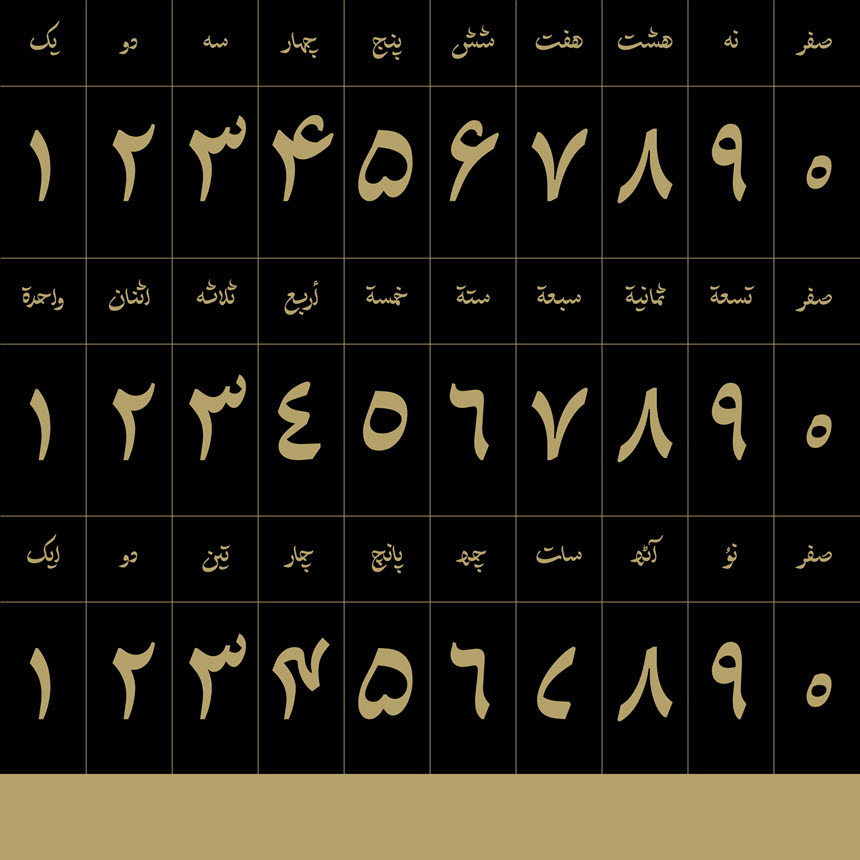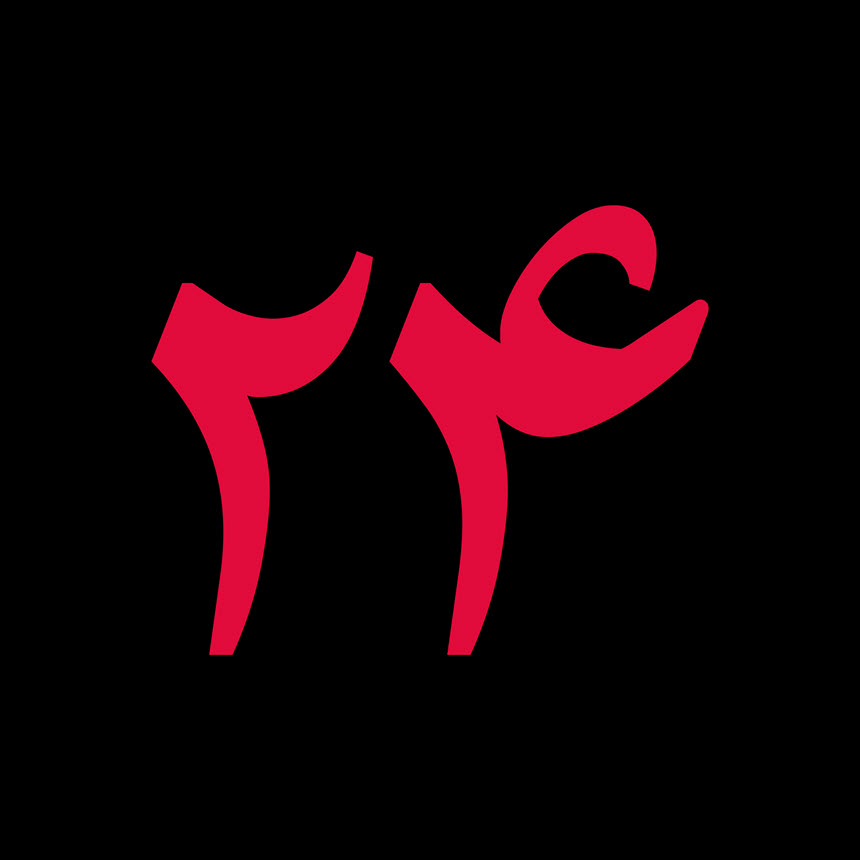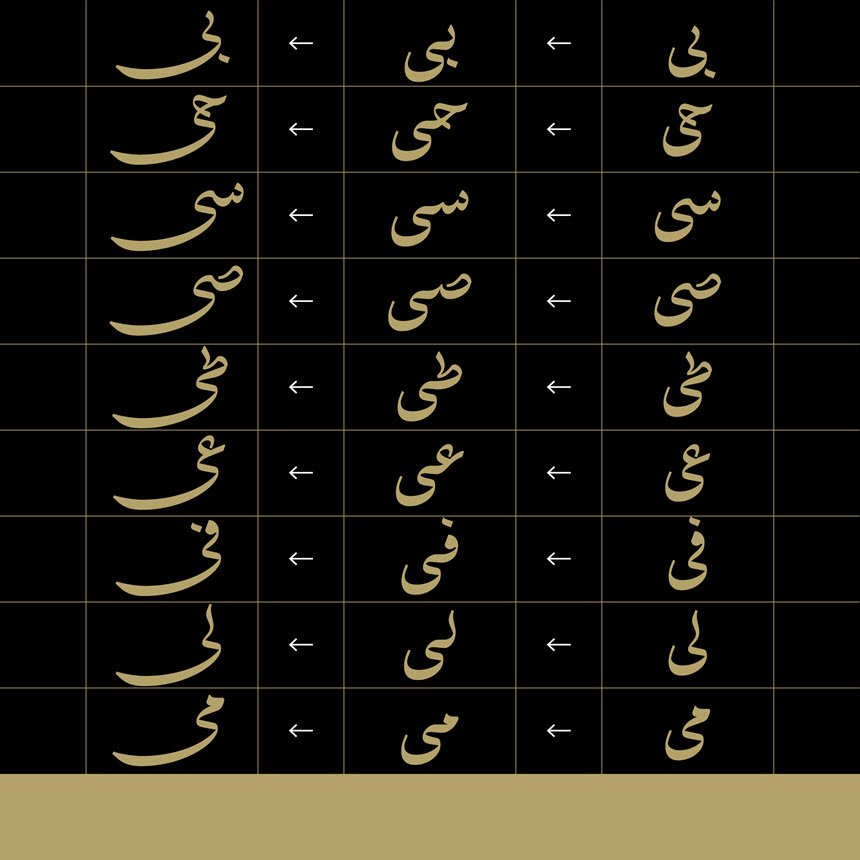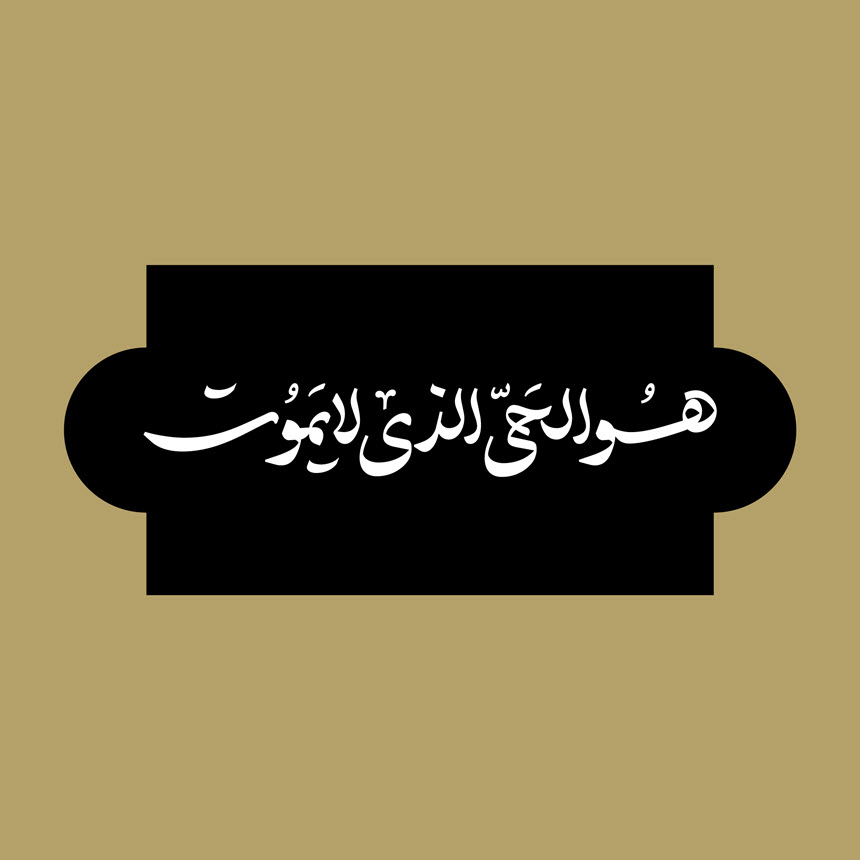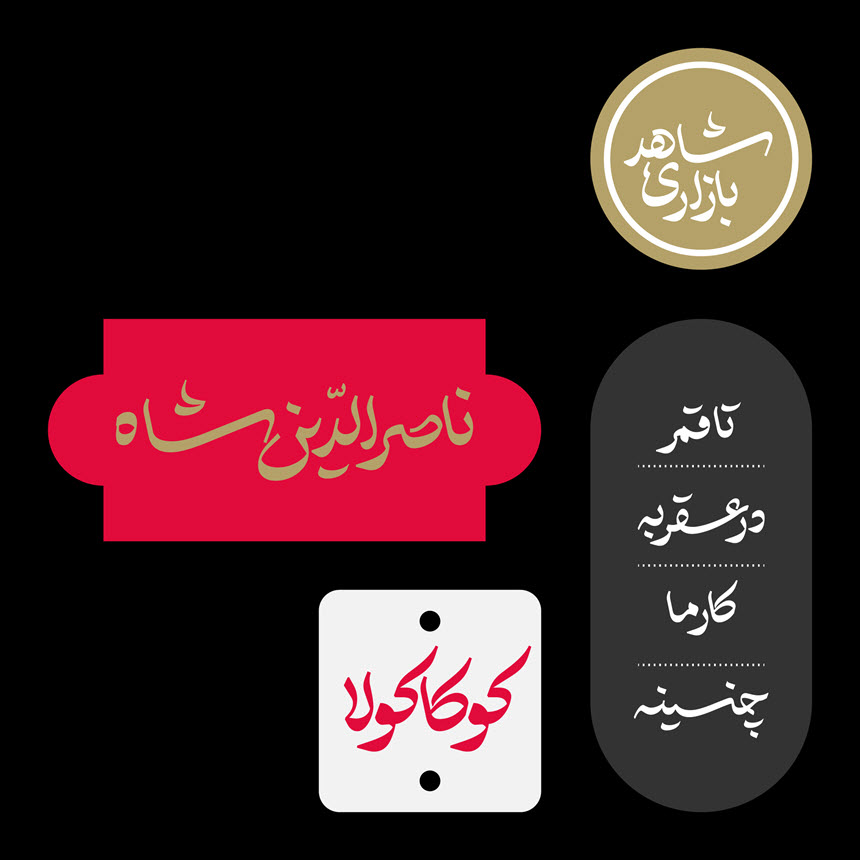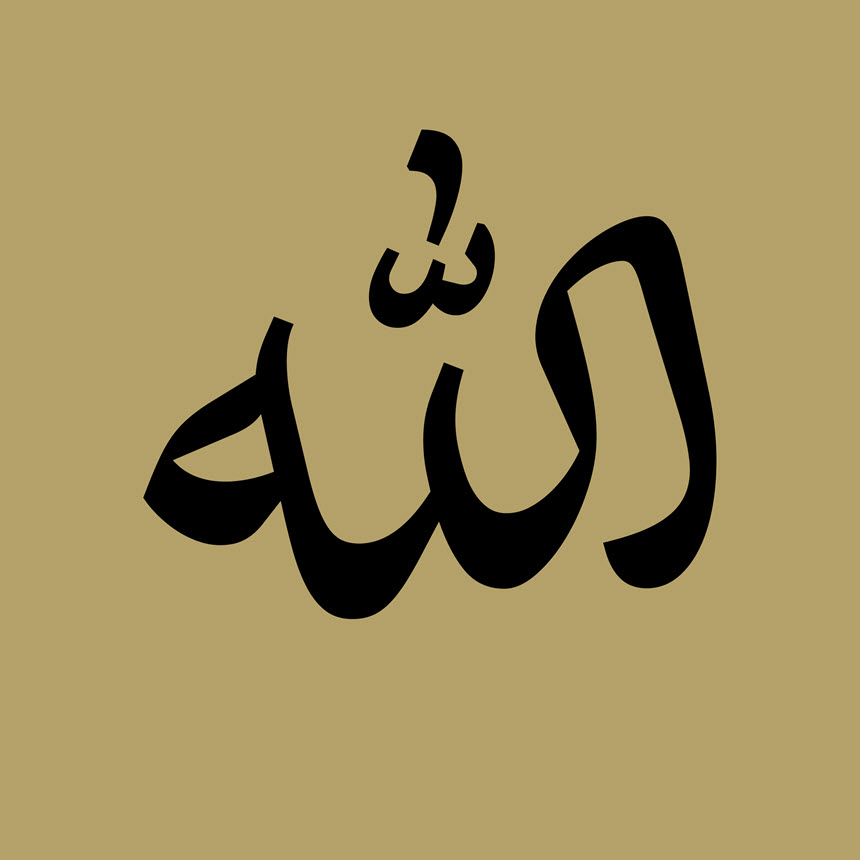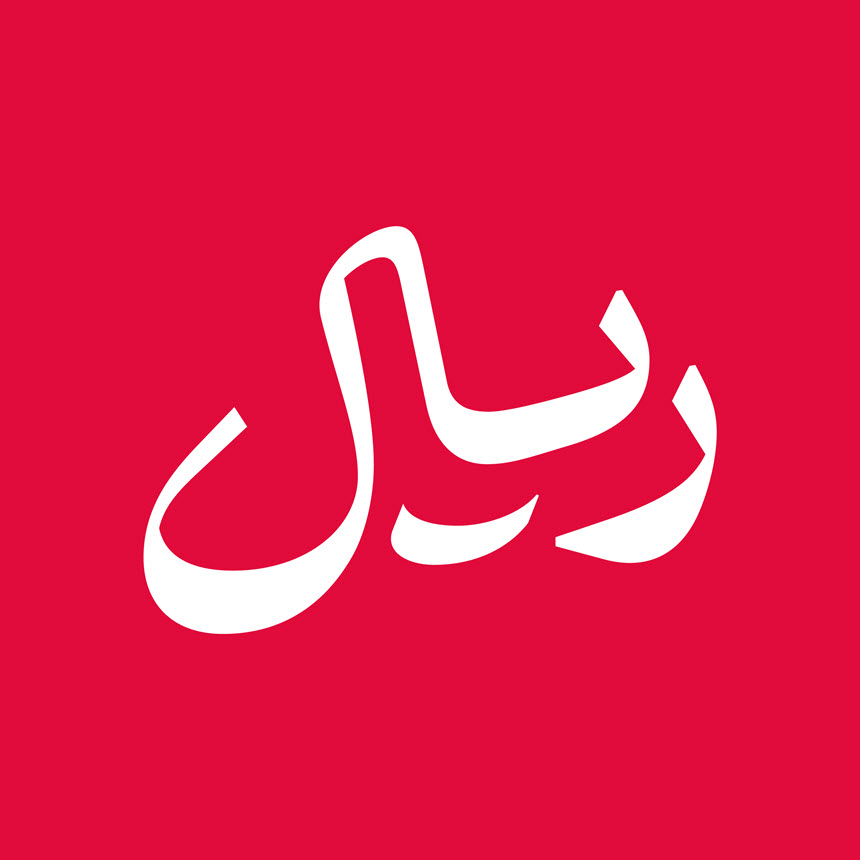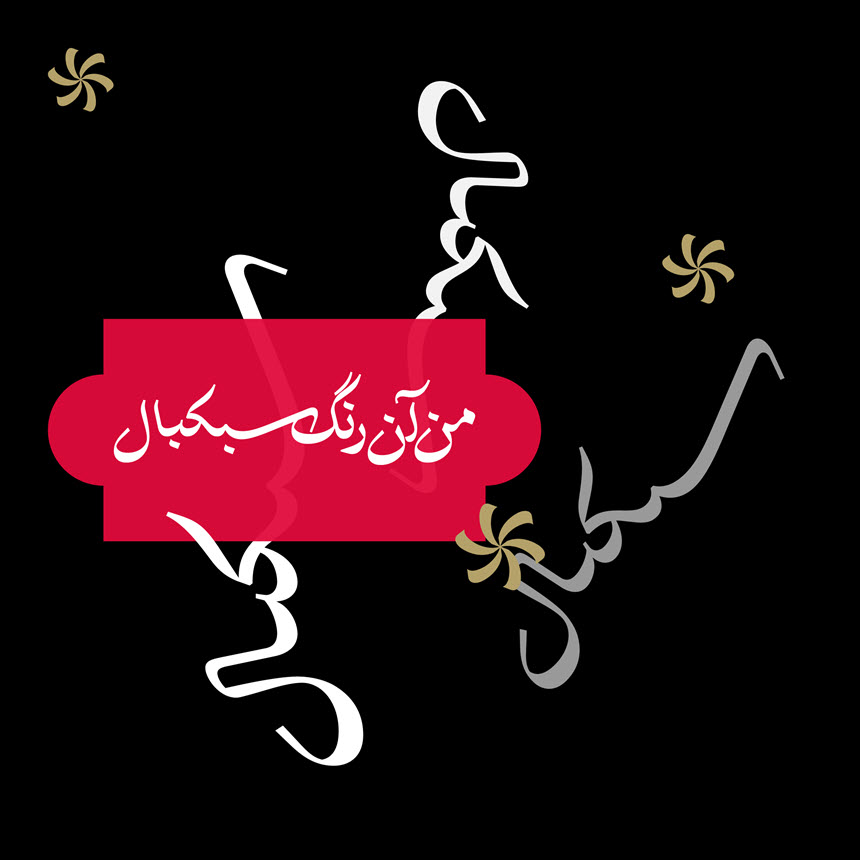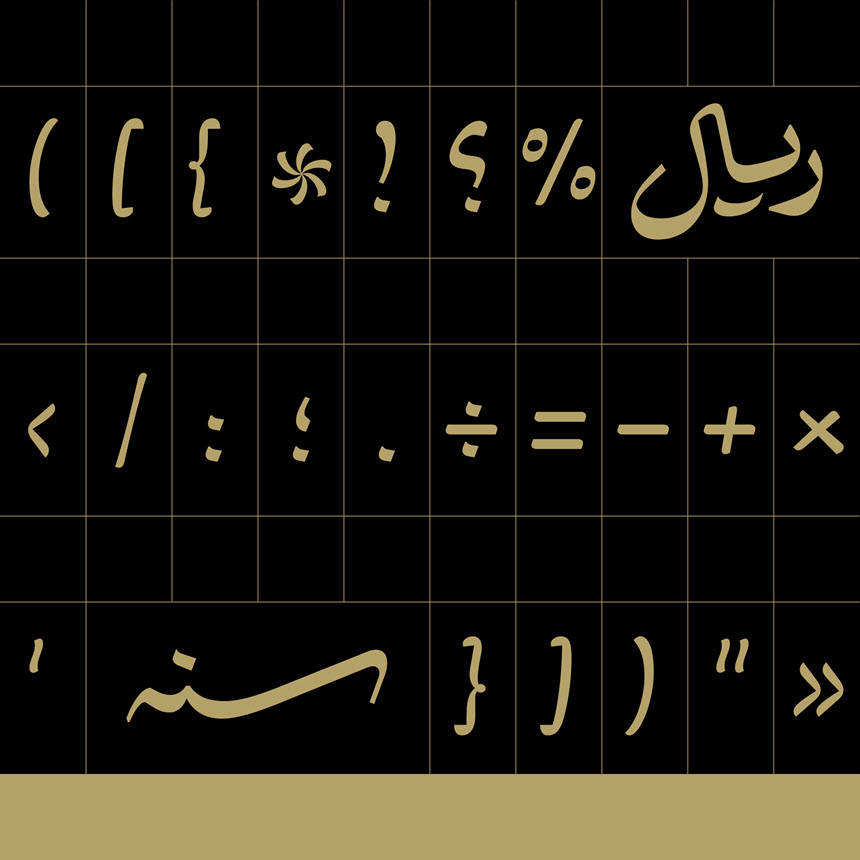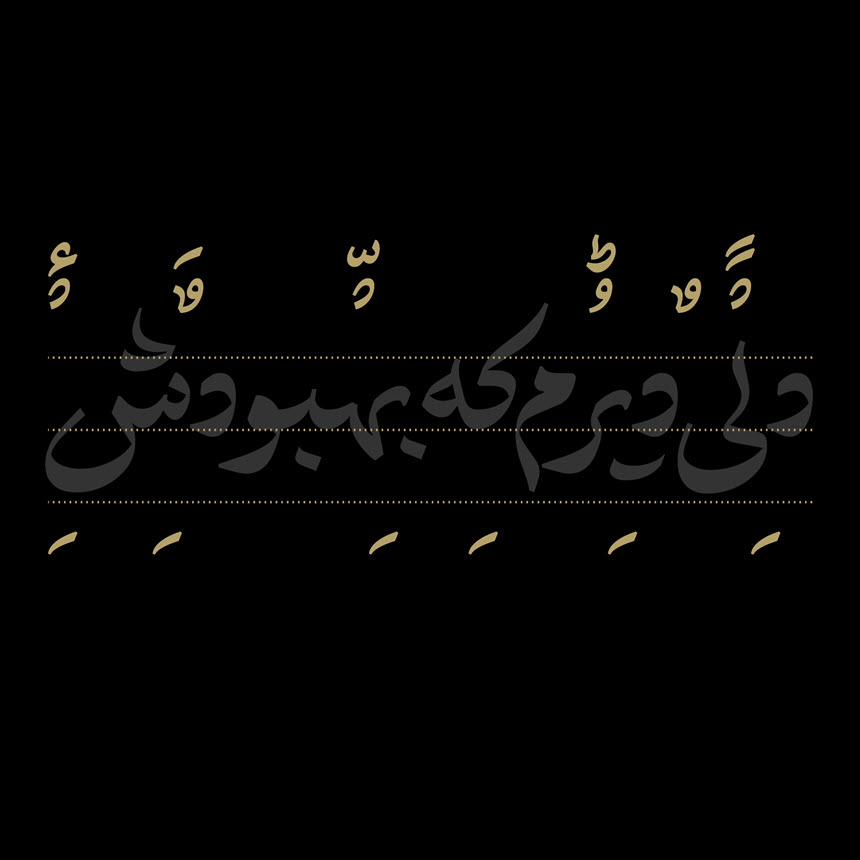
قلم اختیار font Ekhtiar
قلم اختیار
کاری از امیر مهدی مصلحی
درباره قلم اختیار
خط تعلیق یکی از خطوط مهم خوشنویسی ایرانی است. سیر تکامل این خط از «عصر زرين اسلامی» در سده‌های چهارم و پنجم هجری قمری در ایران آغاز و در سده‌های هشتم و نهم به اوج شکوفایی خود می‌رسد. از ویژگی‌های این خط پیچیدگی و پیوسته‌نویسی در تحریر کلمات است. این خصلت‌های پیچیدگی، پیوسته‌نویسی و اتصال کلمات به هم در شیوۀ «شکستۀ تعلیق» تا جایی پیش می‌رود که مرز میان کلمات به روشنی قابل تشخیص نیستند.
خط تعلیق را برآمده از آمیزش خطوط توقیع و رقاع می‌دانند و از این جهت که غالباً برای نوشتن متون فارسی به کار برده می‌شده است، آن را نخستين خط ایرانی پس از اسلام قلمداد می‌کنند. اگرچه در برخی منابع این خط را متأثر از خطوط ایرانیان پیش از اسلام نظیر «پهلویِ کتابی» می‌دانند اما نمی‌توان باقاطعیت در این باره ایراد نظر کرد چرا که از نُسخ خطی نگاشته‌شده به پهلوی کتابی در سده‌های نخستِ استیلای اسلام در ایران فعلاً مکتوبی در دسترس نیست؛ چیزی که روشن است میان منابع موجود به خط پهلوی کتابی و نسخ خوشنویسی‌شده به خط تعلیق شباهت ظاهری چندانی وجود ندارد. کاربرد خط تعلیق در نگارش نامه‌های دیوانی و احکام حکومتی بوده است و به همین جهت به آن خط «تَرَسُّل» نیز می‌گفتند. از خوشنویسان مطرح این خط می‌توان به «احمد ابن علی شیرازی (سدۀ هشتم ق.)، سلطانعلی مشهدی و درویش عبدالله منشی بلخی (سدۀ نهم)، خواجه اختیار منشی گنابادی (سدۀ نهم و دهم)، خواجه میرک منشی کرمانی (سدۀ دهم)، اسکندربیگ ترکمان منشی (سدۀ یازدهم)، محمدکاظم واله اصفهانی (سدۀ سیزدهم) و لطفعلی صدرالأفاضل (سدۀ سیزدهم) اشاره کرد.
بعد از وضع‌شدن خط نستعلیق از ادغام دو خط نسخ و تعلیق، خط تعلیق به تدریج رونق خود را از دست داد تا جایی که در سدۀ اخیر تقریباً به فراموشی سپرده شده بود.
طراحی قلم بر پایۀ خط تعلیق باتوجه به شرحی که از این خط رفت کاری دشوار و در ابتدا ناممکن به نظر می‌رسید. انگیزۀ اصلی طراحی این قلم، بازتاب بخشی از زیبایی‌های این خط در کاربرد امروزی بود. با همین توجیه در ابتدا سعی را بر آن گذاشتم که به خوانشی روزآمد از این خط نیل کنم. نخست، از طرح این پرسش شروع کردم که «اگر بخواهم بنا به مقتضیات امروزی برای نگاشتن متون ادبی سده‌های هفتم و هشتم نظیر سعدی و حافظ قلمی طراحی کنم، چه ویژگی‌هایی را باید مد نظر قرار دهم و استفادۀ مستقیم از خوشنویسی چقدر ممکن است؟» مراحلی که در طراحی این قلم طی کردم:
۱. مشق‌ خط از روی نسخه‌های خطی خواجه‌اختیار، واله اصفهانی و کتاب رسم‌الخط تعلیق (اثر ارزشمند هنرمند گرانقدر حسین فیض‌آبادی)
۲. طراحی آزاد برپایۀ آموخته‌های تعلیقی و تحریر جملات کوتاه
۳. اجرای کامپیوتری طراحی‌های منتخب و سعی در توسعۀ حروف باتوجه به هدف اولیه
۴. جای‌گذاری حروف در نرم‌افزار طراحی تایپ و حل مشکلات همنشینی
۵. ویرایش قلم بعد از خروجی‌های مختلف و آزمودن آنها در متن
در روند طراحی این قلم بسیار از نمونه‌های خوشنویسی «خواجه اختیار منشی گنابادی» بهره بردم؛ به همین علت برای پاس‌داشت نام او و با موافقت نرم‌افزاری مریم، این قلم «اختیار» نامیده شد. به‌طورکلی در توصیف قلم اختیار می‌توان گفت، قلمی است در بازۀ خوشنویسی و قلم‌های هندسی، پر دور، خمیده، زوایای حروف در همنشینیِ کلماتْ مکمل همدیگرند و حروف مطابق استاندارهای امروزی طراحی قلم اجرا شده‌اند.
در خاتمه، امیدوارم این قلم ابزاری کاربردی برای طراحان گرافیک خط فارسی/عربی باشد و بهانه‌ای شود برای کندوکاو بیشتر در دیگر خطوط خوشنویسی ایرانی و فرهنگ‌های نوشتاری مرتبط به جهت رسیدن به پاسخ‌های طراحانۀ روزآمد.
امیر مهدی مصلحی
امیرمهدی مصلحی، متولد ۱۳۶۸، طراح حروف، خوشنویس و پژوهشگر ایرانی است که در آلمان سکونت دارد. او دانش‌آموختهٔ کارشناسی معماری از دانشکدهٔ هنرهای زیبای دانشگاه تهران است و تحصیلاتِ خود در طراحیِ حروف را در کشور فرانسه، مرکز ملی تحقیقات تایپوگرافیک* در دورهٔ پست‌مستر مدرسهٔ ملی هنر و دیزاین نانسی تکمیل کرده و پس از آن مشغولِ تحصیل در مقطع کارشناسی ارشدِ مطالعاتِ فرهنگ‌های مصنوعات نوشتاری و نسخ خطی در دانشگاه هامبورگ** شده است. کارهای طراحی حروف او محصول پژوهش‌های عمیق در نسخ خطی و آثارِ خوشنویسی است. برخی از قلم‌های او در ایران توسط نرم‌افزاری مریم منتشر شده است. در سال‌‌های اخیر نیز سابقهٔ همکاری با شرکت‌های مطرحِ جهانی طراحی حروف، نظیر Typotheque، TPTQ Arabic، Rosetta و دیگر مجموعه‌ها داشته است.
*Atelier National de Recherche Typographique
** Centre for the Study of Manuscript Cultures